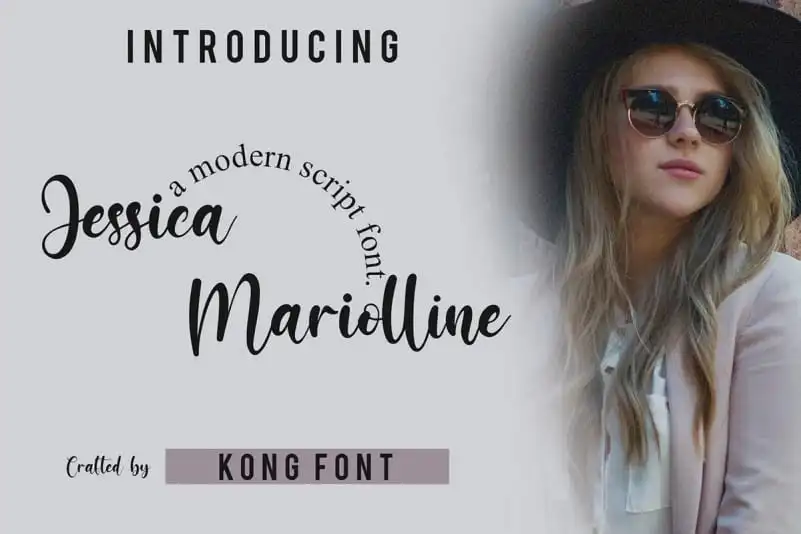
Jessicca Mariolline Script Font – Download Grátis
A “Jessicca Mariolline Script Font” é uma criação incrivelmente delicada e envolvente para aqueles que buscam um acabamento único no design de textos. Inspirada nas linhas naturais dos rascunhos com pincel, essa fonte traz uma sensação orgânica e natural que se assemelha à própria escrita por mãos humanas. O designer, sem dúvida, fez questão de incluir muitas ligaturas para garantir que cada palavra tenha um toque único e autêntico, criando a aparência desejada de uma escrita feita à mão livre. Com sua forma fluida e harmoniosa, esta fonte não apenas é uma escolha perfeita para gráficos de design editorial ou identidade visual, mas também oferece um toque natural que pode ser adorado em cartões de aniversário ou outras criações casuais. Essa fonte 99designs é a escolha certa para aqueles que buscam uma aparição sofisticada e ao mesmo tempo descontraída no seu design, mantendo a essência da escrita por mãos humanas.